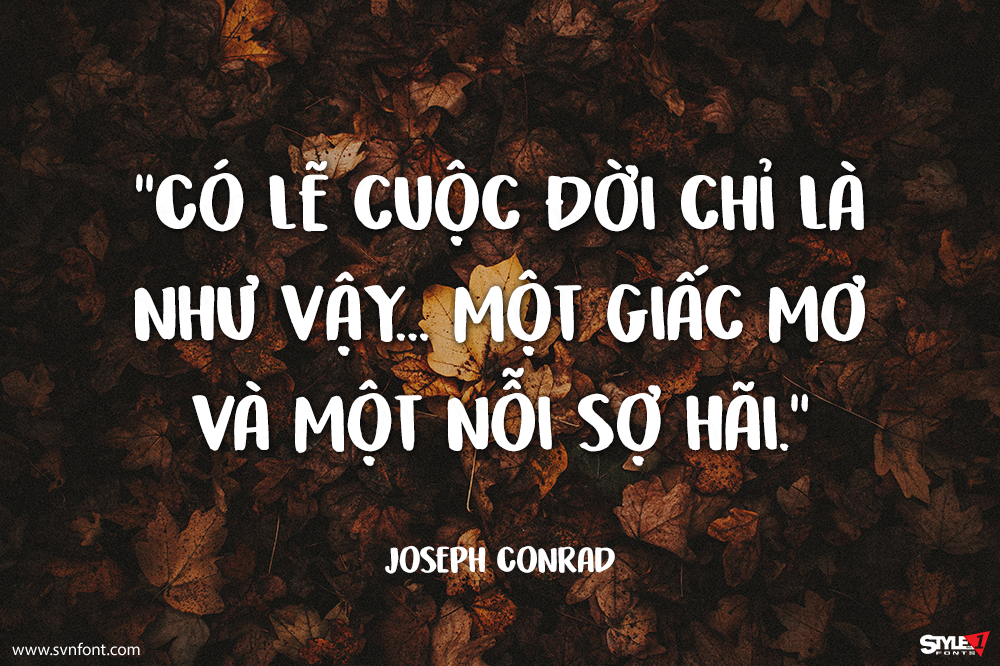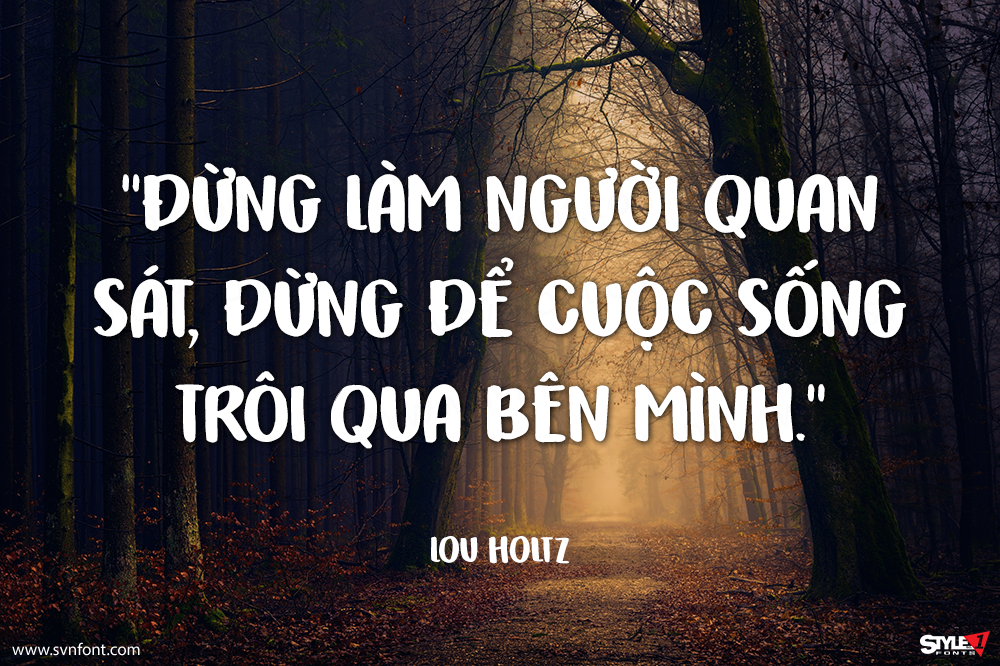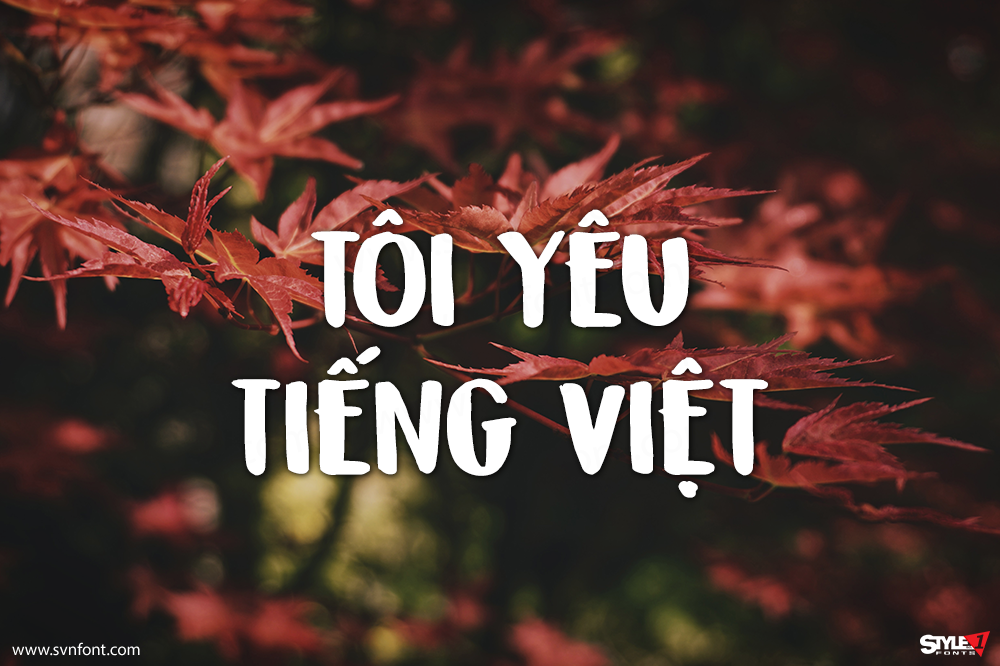
Honeyguide Caps là một bộ font vẽ tay tuyệt đẹp. Bộ này gồm hai kiểu chữ: một font script nét cọ mềm mại và một font in hoa vui nhộn, cả hai đều có phiên bản italic. Bạn có thể kết hợp cặp đôi này cho bao bì sản phẩm, bìa sách, thiệp chúc mừng ngày lễ, hoặc các sản phẩm cần một phong cách đóng gói chất lượng và giàu cảm xúc.
Nhà thiết kế: Hanoded
Nhà phát hành: Hanoded